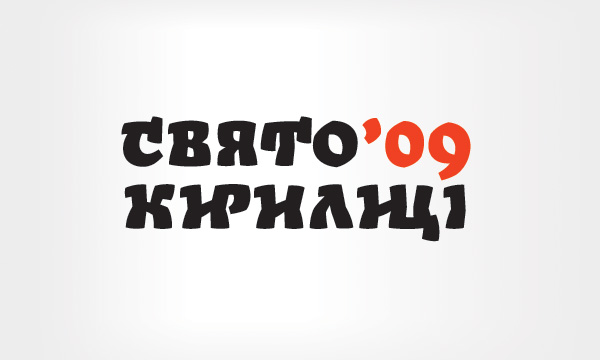
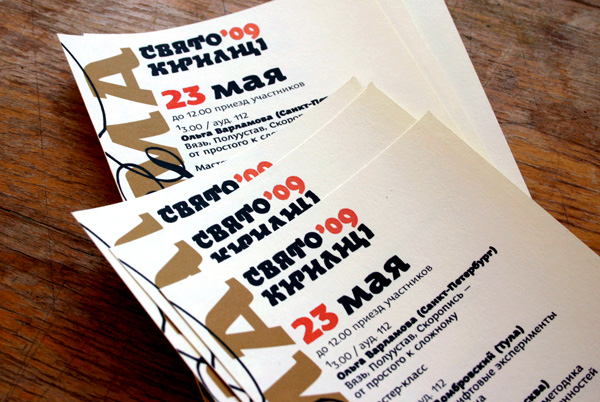
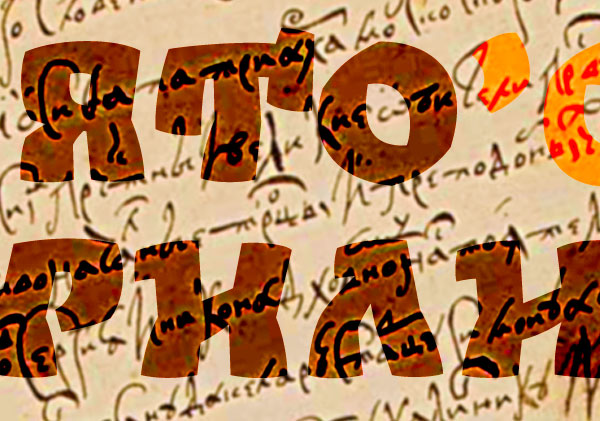
Свято Кирилиці
Логотип ежегодного фестиваля шрифта и каллиграфии «Свято Кирилиці 2009» (Харьков, Украина). Буквы построены на совмещении исторической традиции и современных тенденций. Массивные и грубоватые формы полуустава получили каллиграфические изломы и свежую современную графику. Лигатуры «ИР», «ИЦ» призваны бодрить взгляд и отвечают основной идее фестиваля—вдохнуть в новую кириллицу дух допетровской каллиграфической традиции.